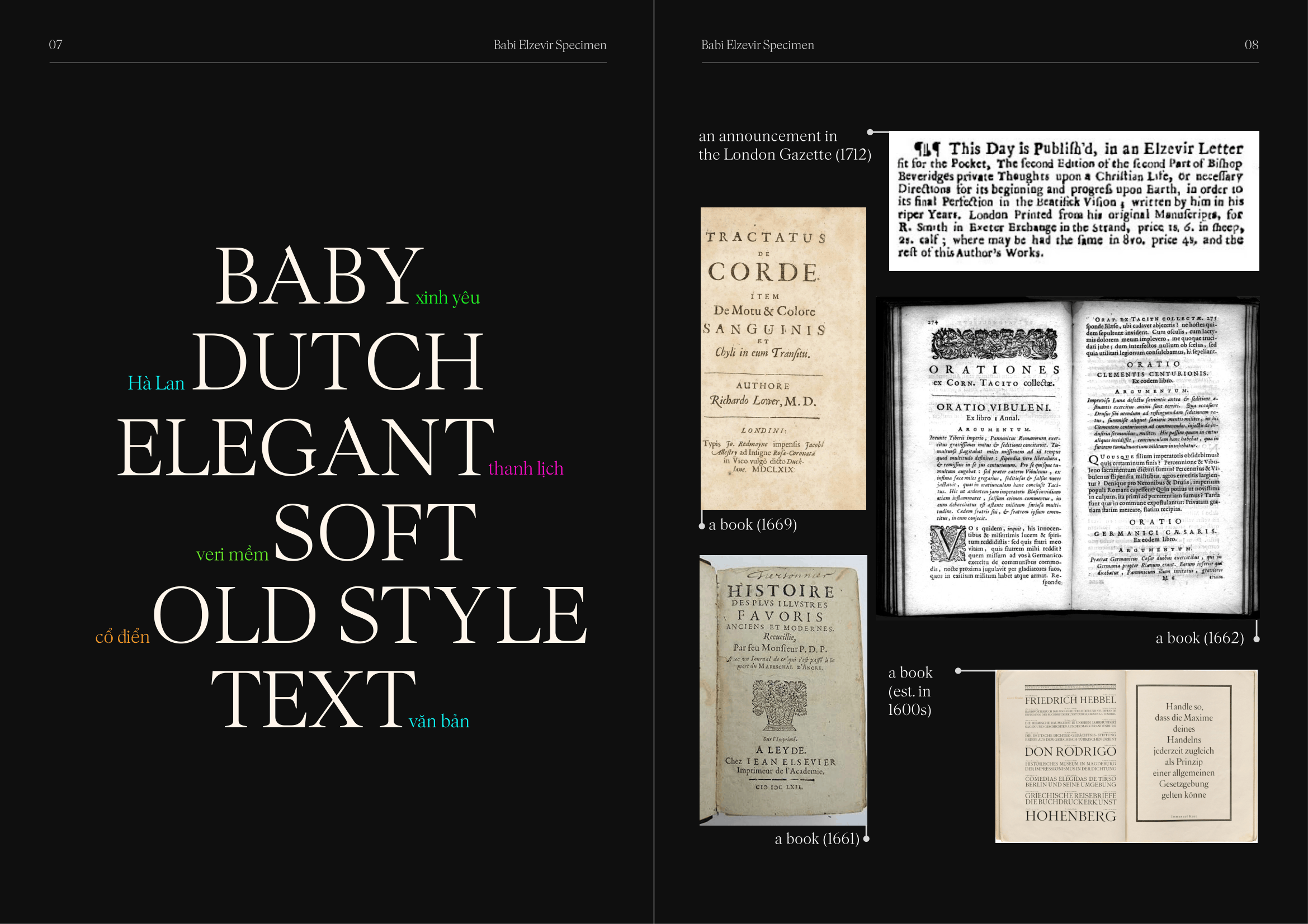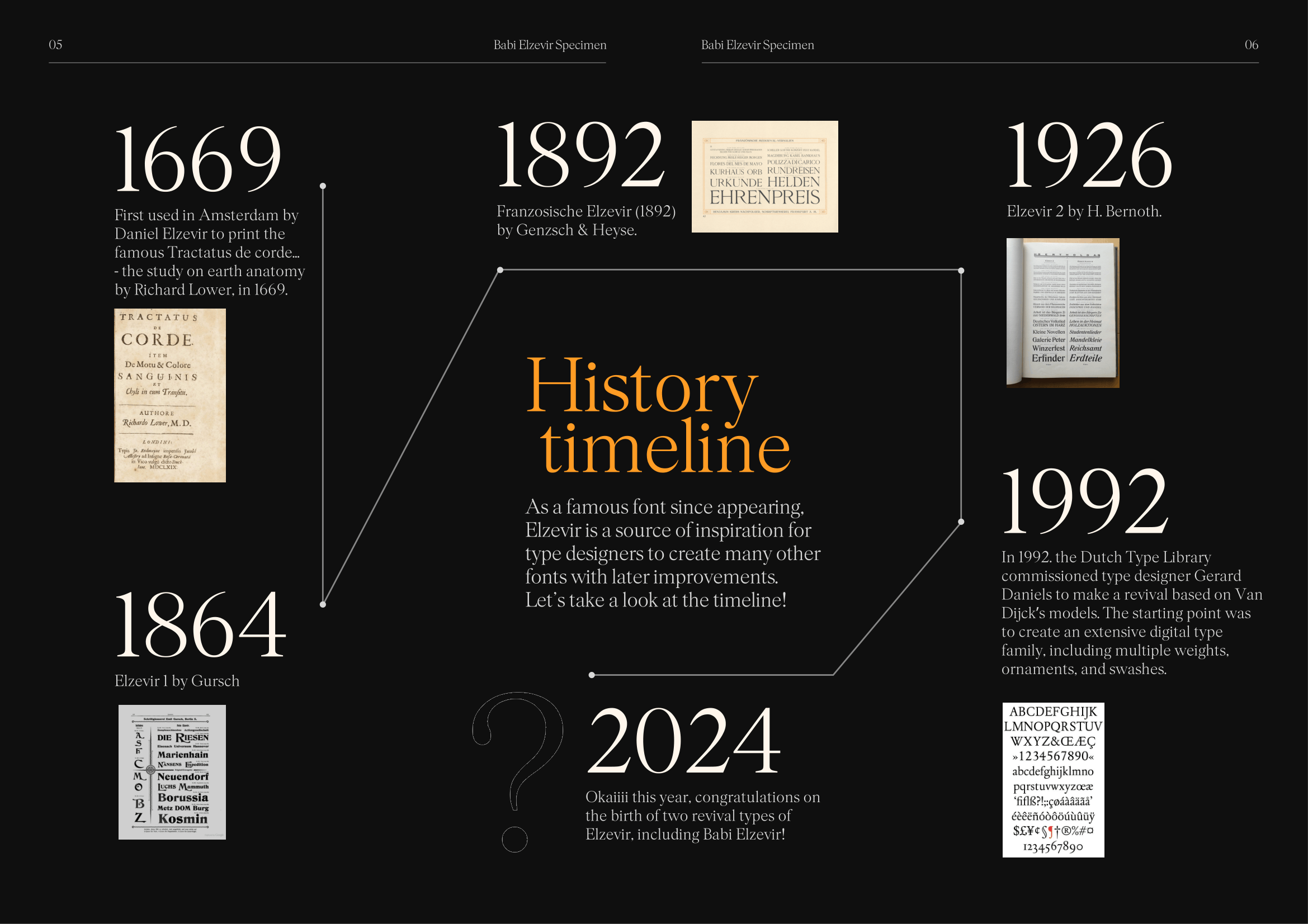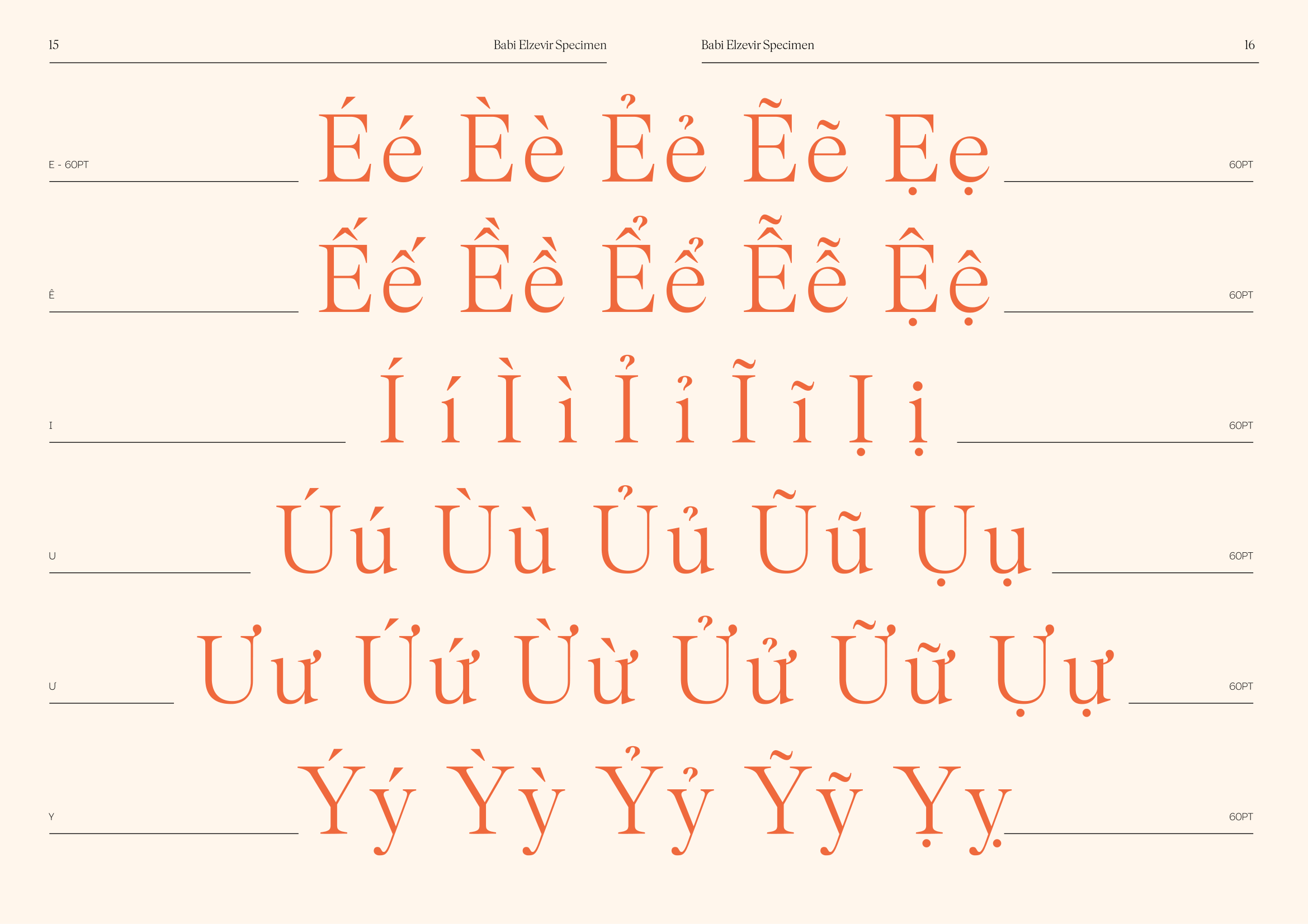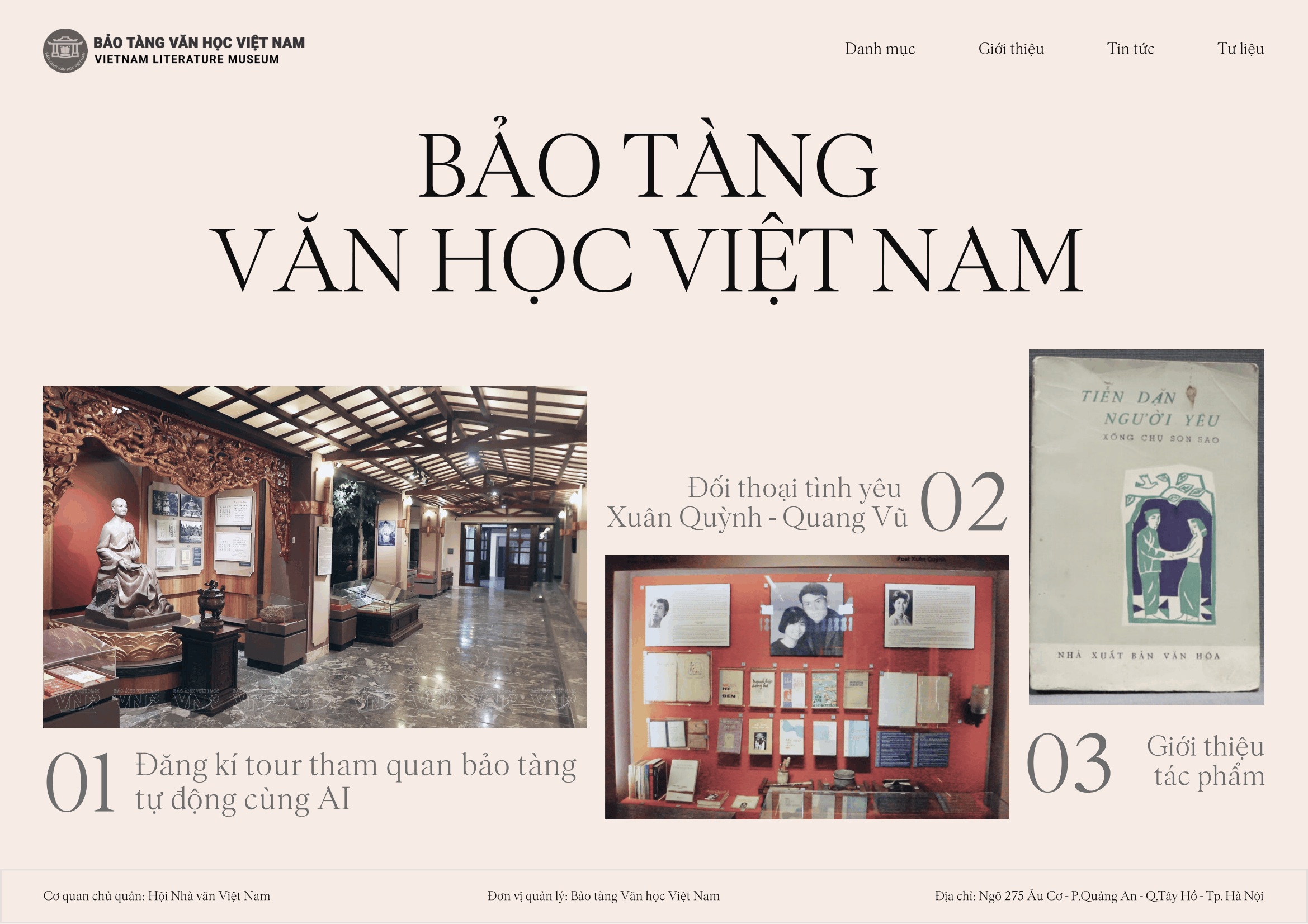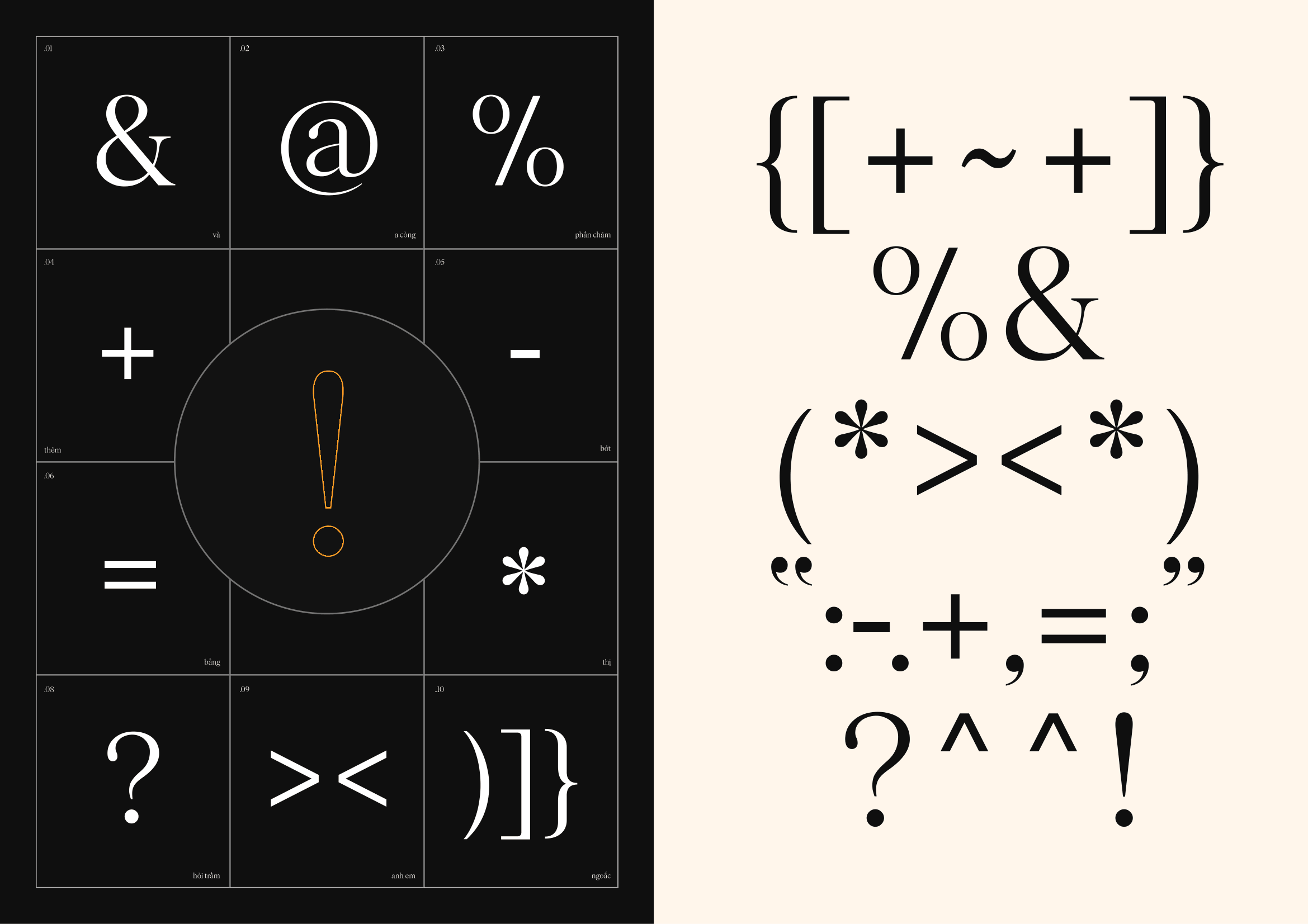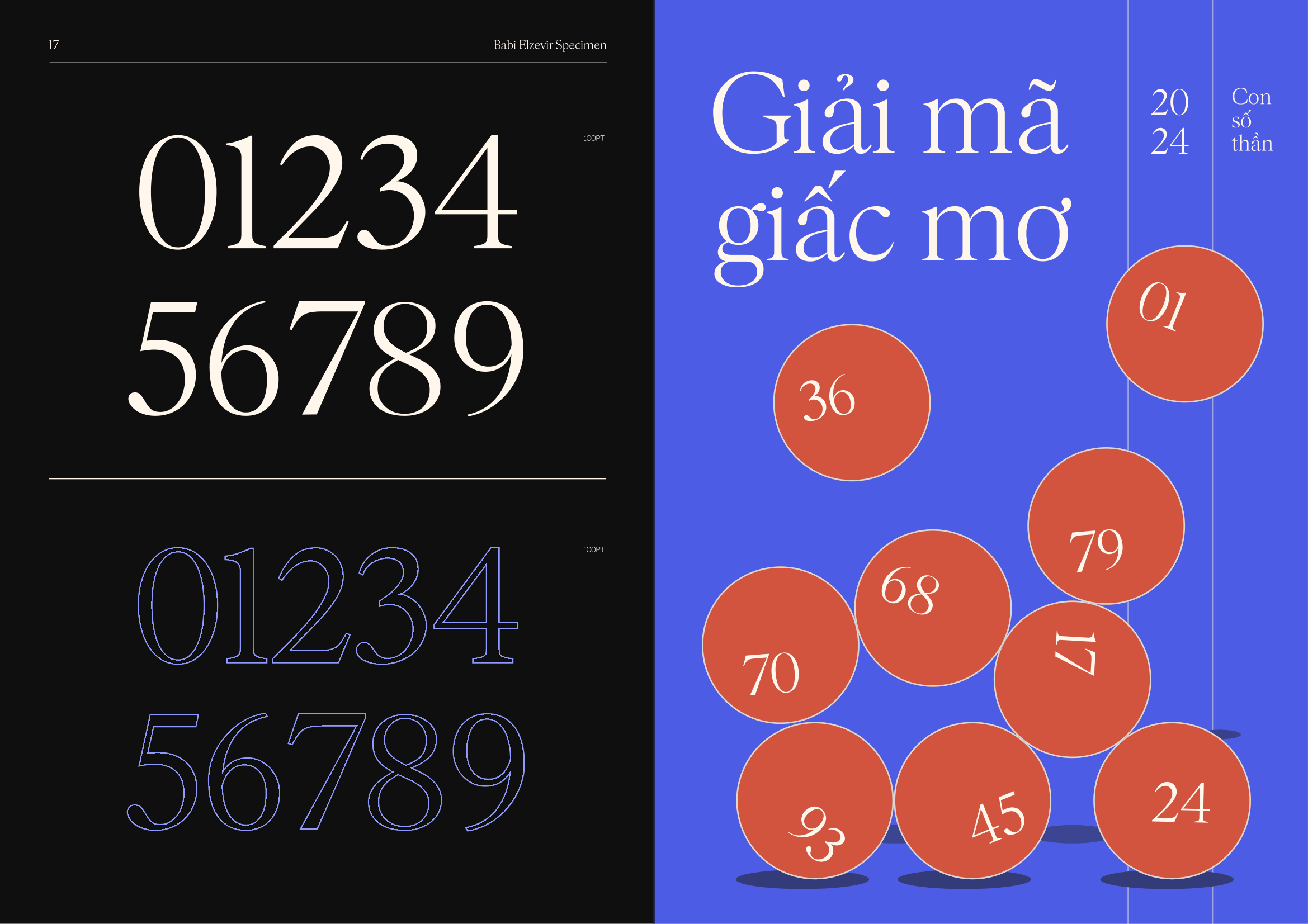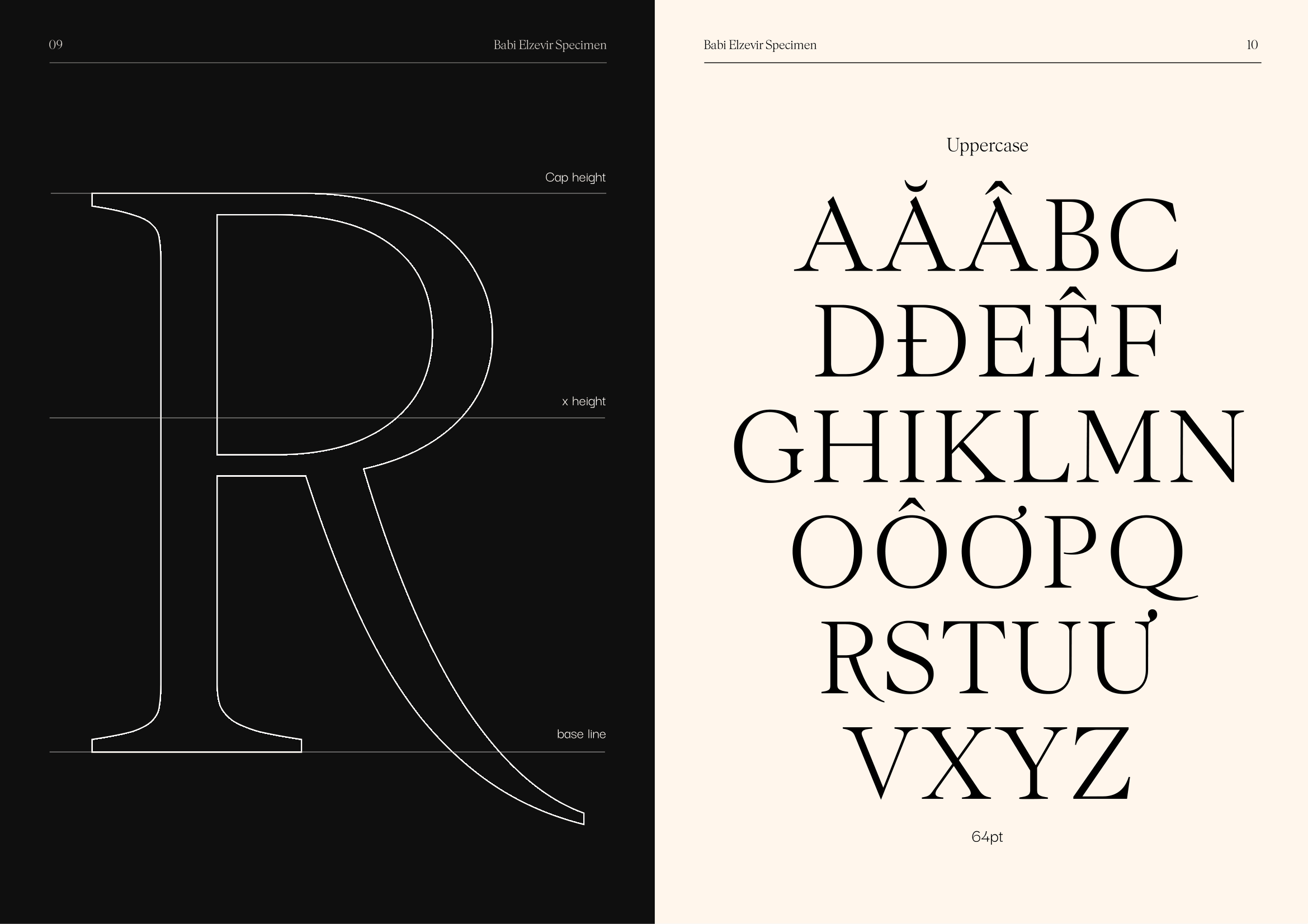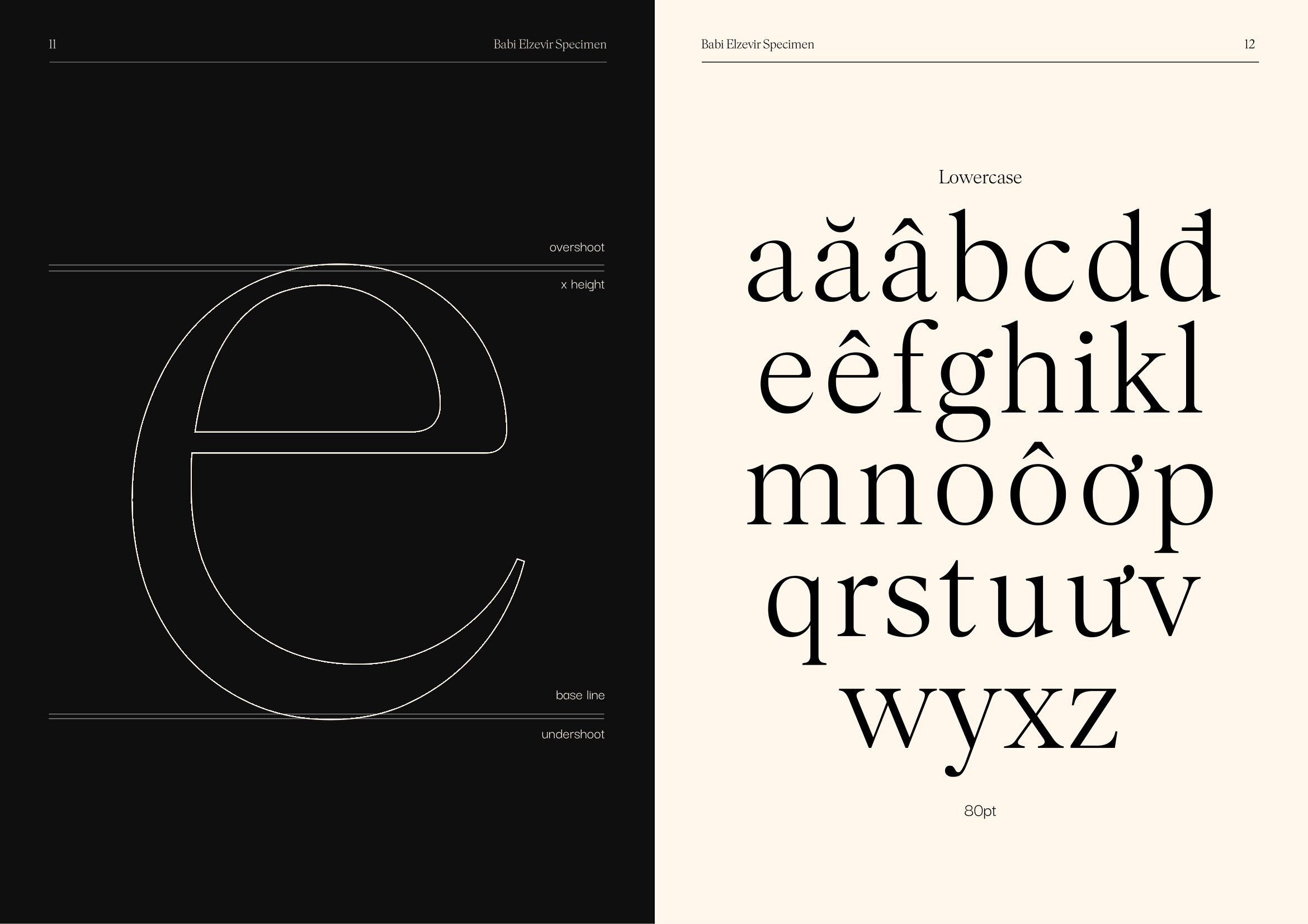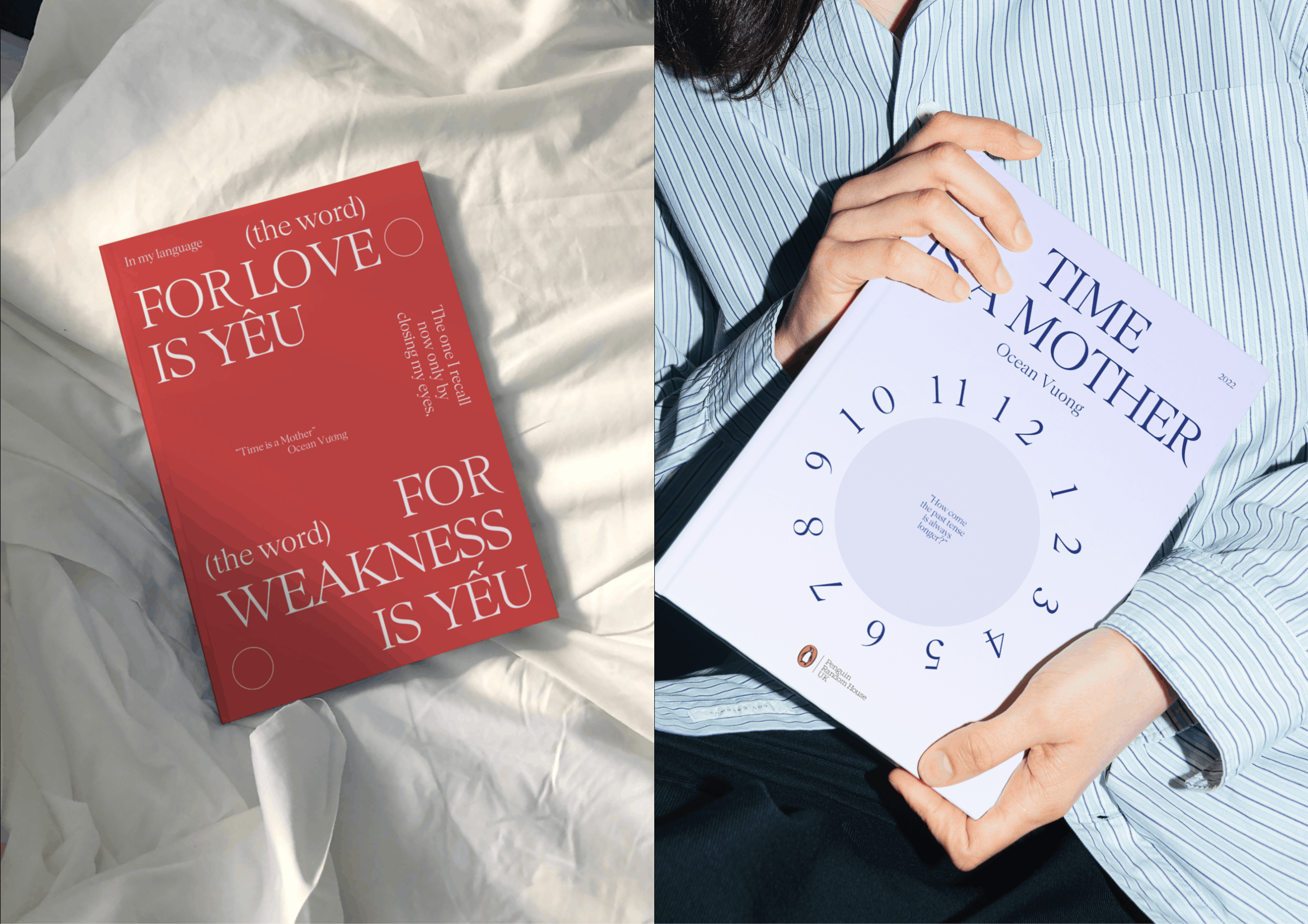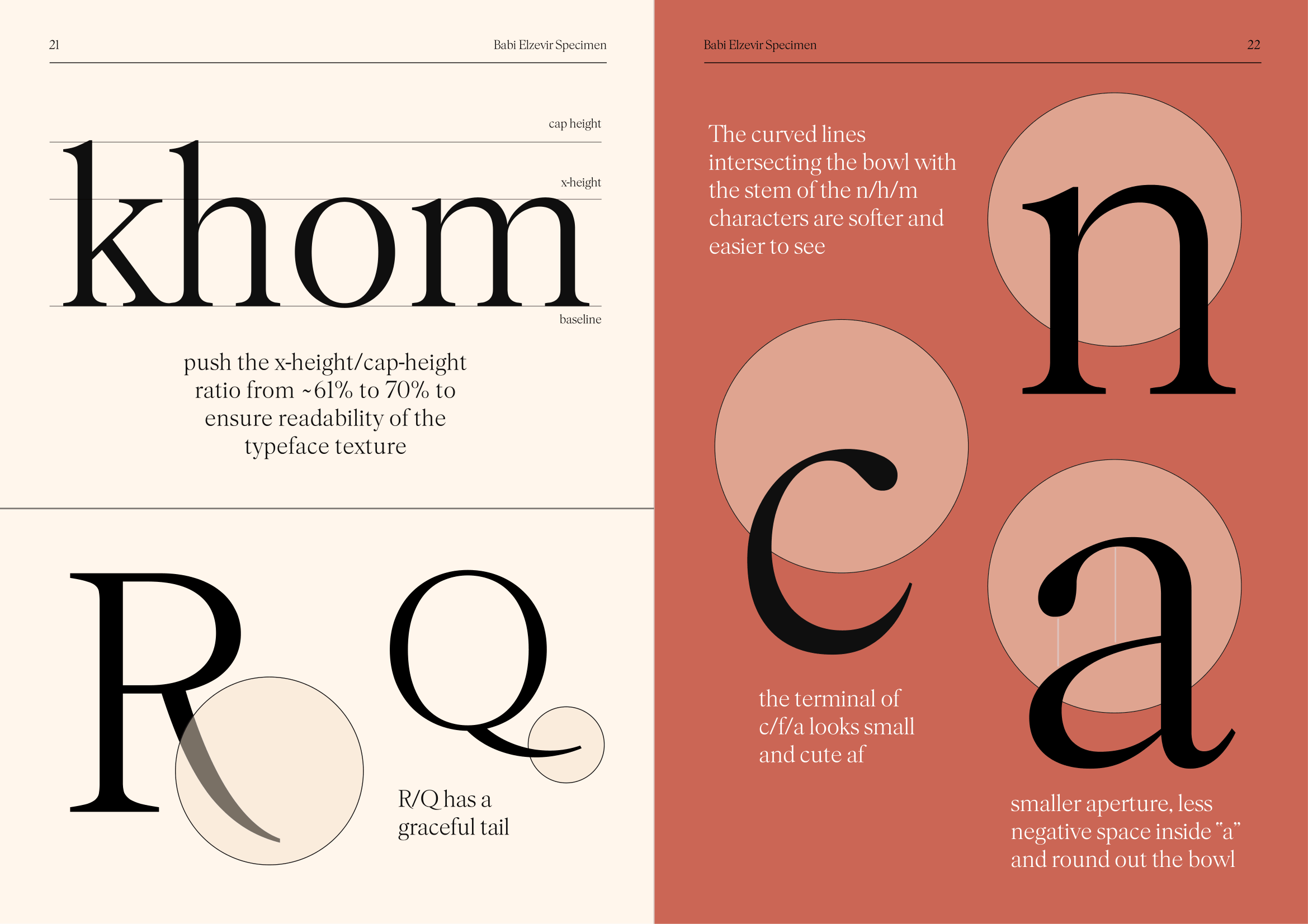
Babi Elzevir
Về Babi Elzevir: Babi Elzevir - con rơi của Elzevir Ancien nhưng là con ruột dứt dạ Phương Mai. Y đúc mẹ, Babi nhẹ nhàng, thỏ thẻ và duyên dáng đắm mình trong văn chương và thi ca của nhân loại.
Old Style Serif
Text
Phương Mai
Elzevir Ancien is a typeface produced by the Elzevir family, the largest printing house in the Netherlands during the Renaissance - Baroque period.
Elzevir first appeared in printed works in 1669 (some claim it dates back to 1662). The typeface was created by the punch cutter - Christoffel van Dijck - who is considered one of the greatest punch cutters of his time. Elzevir was used for many book in the Elzevir printing house and later became famous throughout Europe for its readability, even considered the most beautiful typeface of its time, while some others considered it as boring like Dutch people.